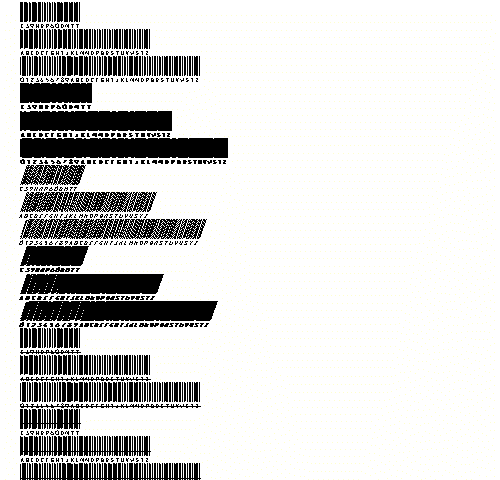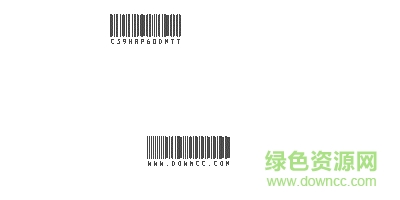
C39HrP60DmTt
C39HrP60DmTt是一款條形碼字體,字體一般可用于繪圖設(shè)計、廣告創(chuàng)意、包裝印刷、平面設(shè)計等應(yīng)用,這款條形碼字體能夠廣泛使用,各行各業(yè)都可以使用。小編提供都是免費下載!如果你需要的話,趕緊來綠色資源網(wǎng)下載吧!